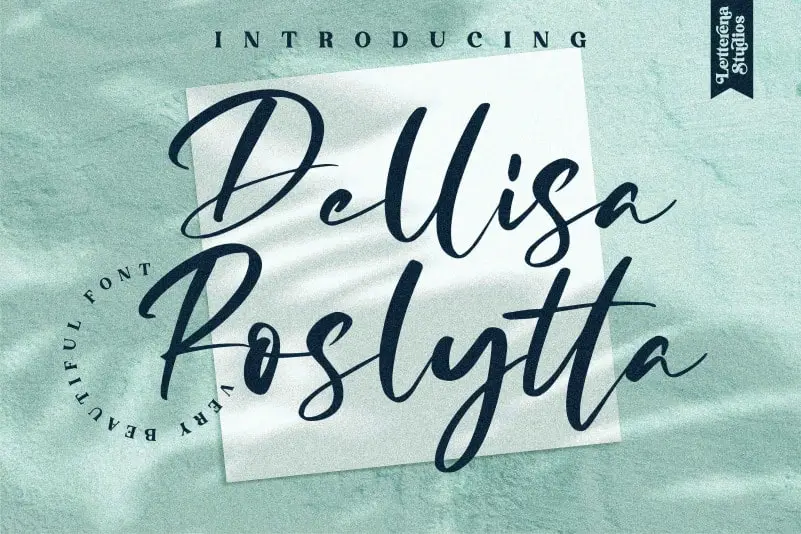
Dellisa Roslytta Script Font – Fonte Grátis
Dellisa Roslytta Script Font
A fonte Dellisa Roslytta Script é uma escolha perfeita para qualquer projeto que busque um toque único e autêntico. Escrevida a mão, esta fonte se destaca no campo das letras manuscritas, proporcionando uma variedade impressionante de opções, desde logotipos até capas de livro. Ideal para uma vasta gama de projetos como design de móveis, embalagens de produtos, têis personalizados, cartões de visita, convites e carteirinhas, Dellisa Roslytta Script oferece um toque pessoal que enriquece qualquer projeto. Seja para a criação de uma capa de livro inspiradora ou uma etiqueta personalizada com delicados traços manuscritos, esta fonte é perfeita para tornar seu trabalho ainda mais especial e autêntico. Ideal para designers gráficos, este script tem um estilo elegante e sofisticado que se adapta perfeitamente a qualquer tipo de projeto visual. Suave e envolvente ao mesmo tempo, Dellisa Roslytta Script é uma fonte certeza que vai ajudar você a criar mensagens memoráveis e personalizadas em todo o seu trabalho. Não hesite em dar vida à sua arte com essa fonte única que transmite um toque cuidadosamente criado.